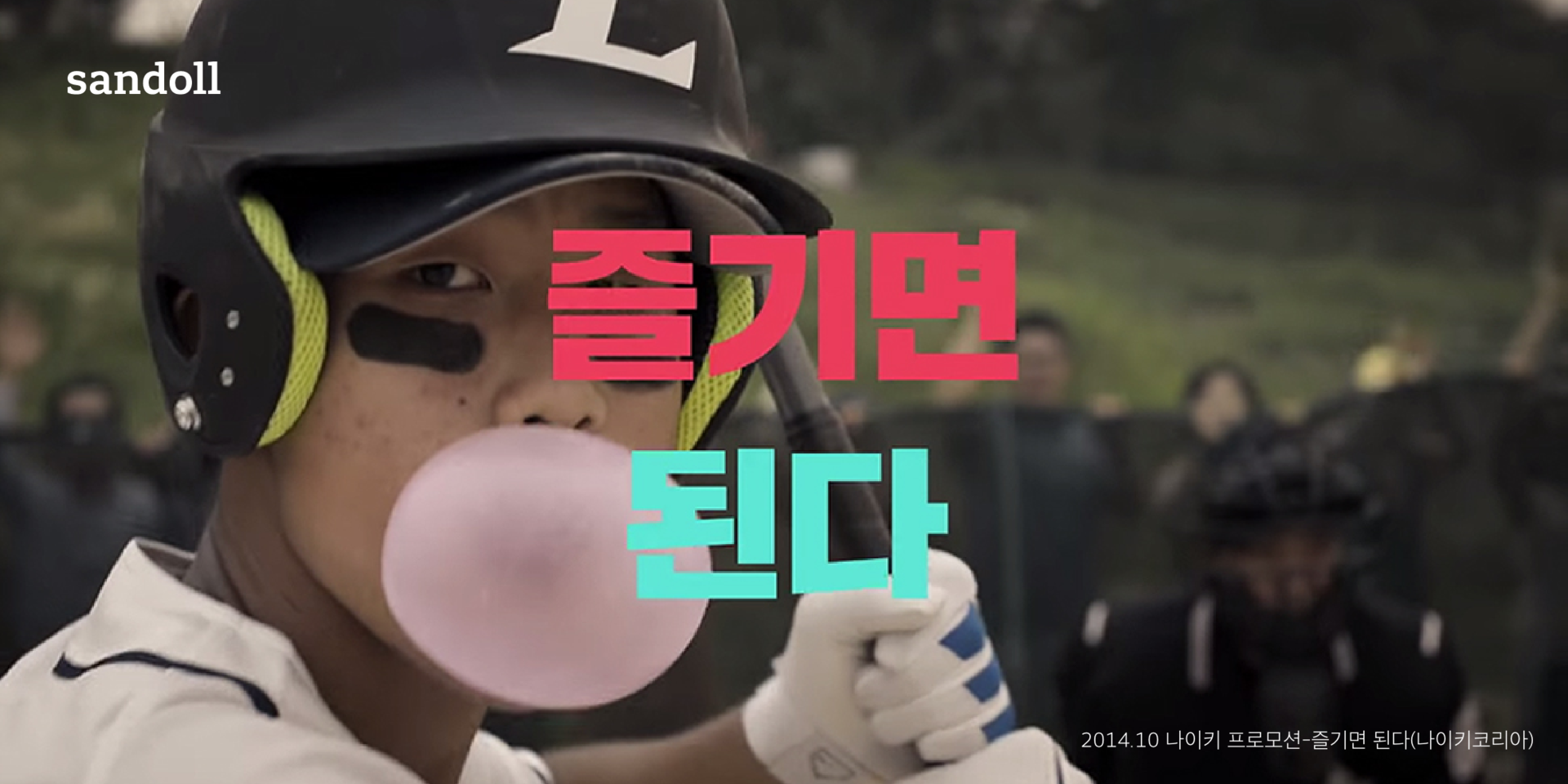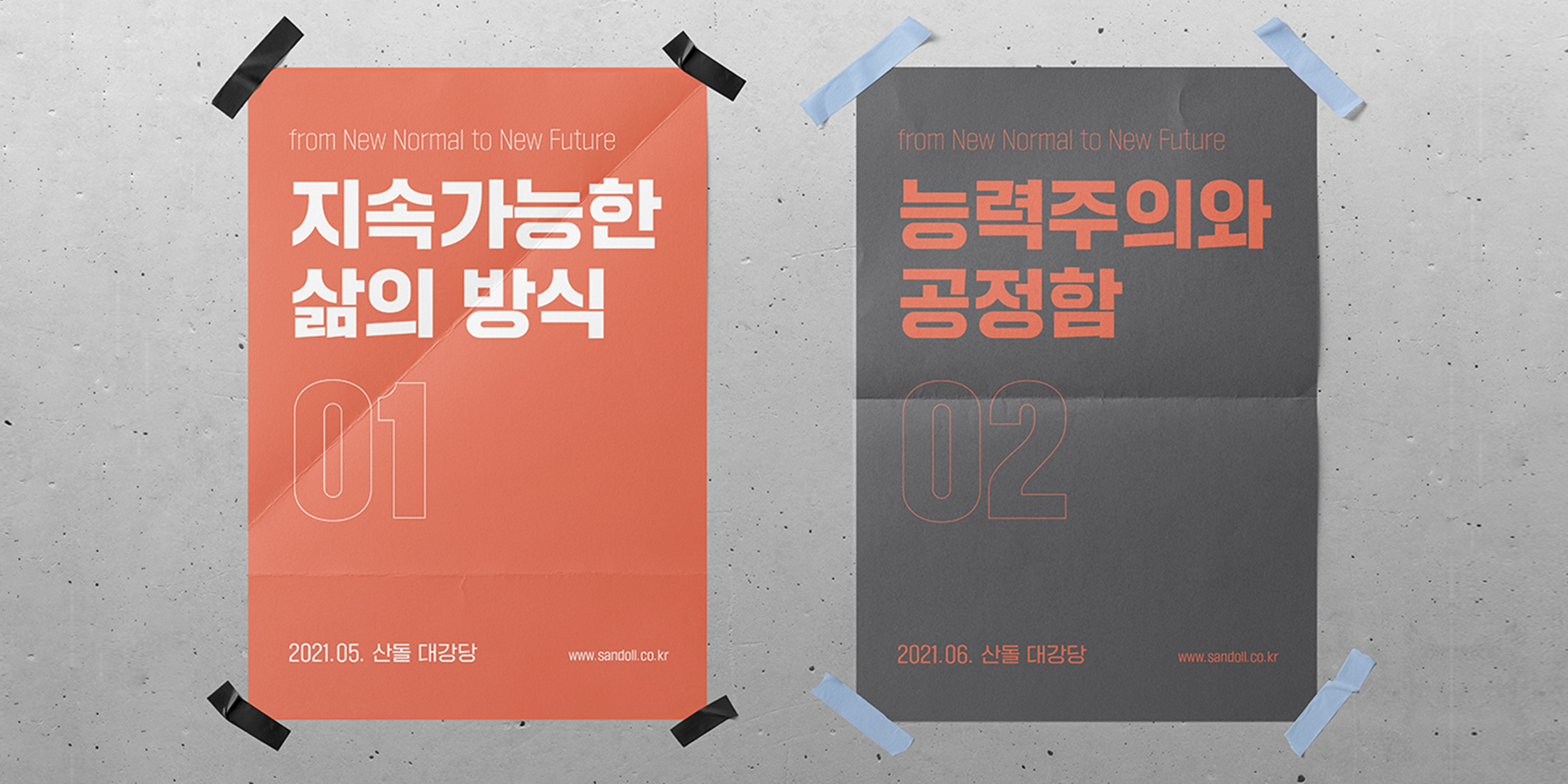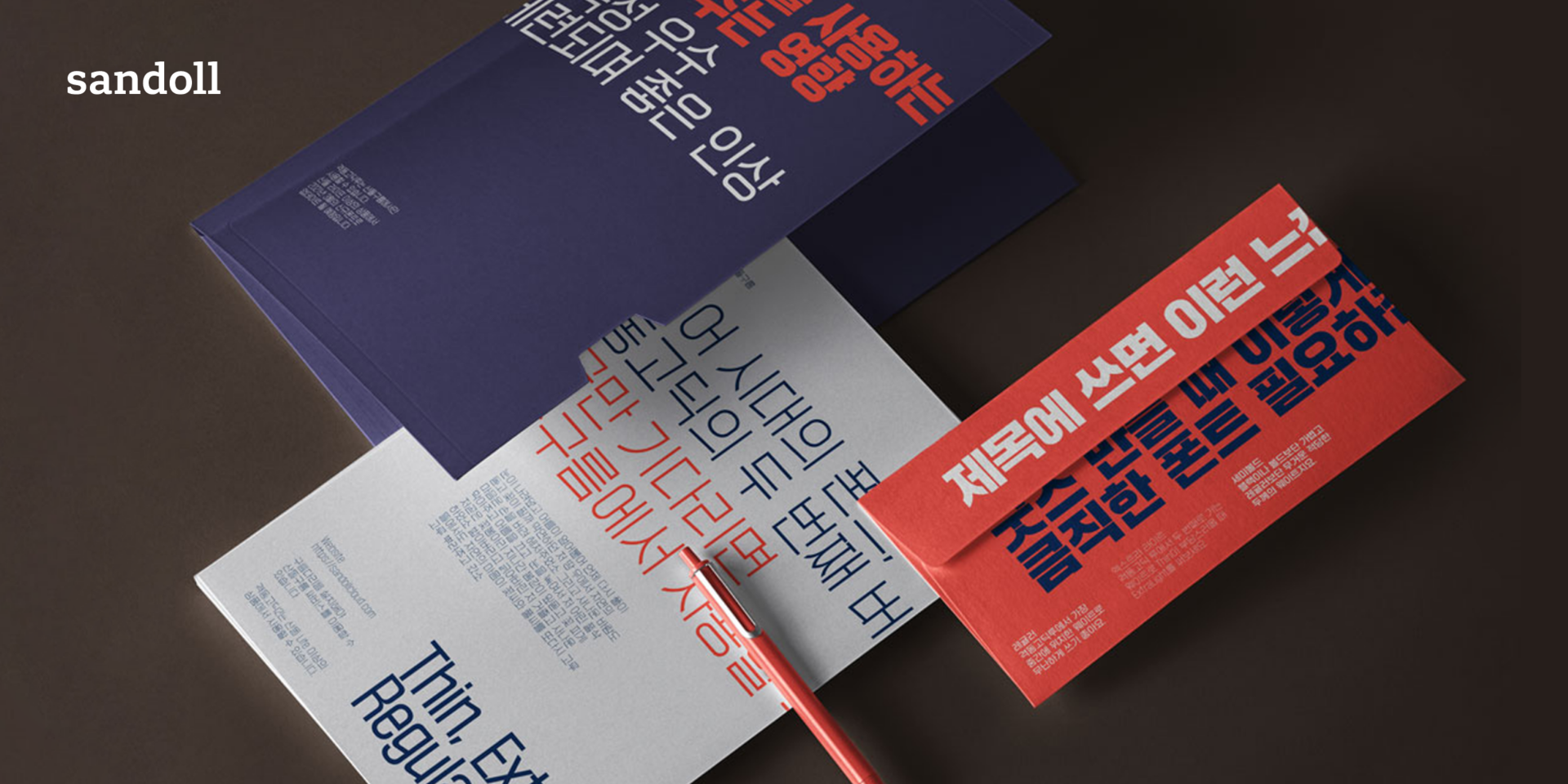
Sandoll 격동고딕
산돌 격동고딕은 격변하는 과도기적 시대상을 현대적 관점으로 재해석한 고딕체 폰트이다.가상바디 안에 꽉 찰 정도의 레터페이스와 굵은 줄기, 날카로운 맺음, 속공간에 따라 변형되는 낱자형태 등을 기본 속성으로 잡고 작업을 진행했으며, 출시 후 압도적 카리스마와 임팩트로 인해 각종 산업군에서 다양하게 사용되는 인기 폰트로 급부상했다.